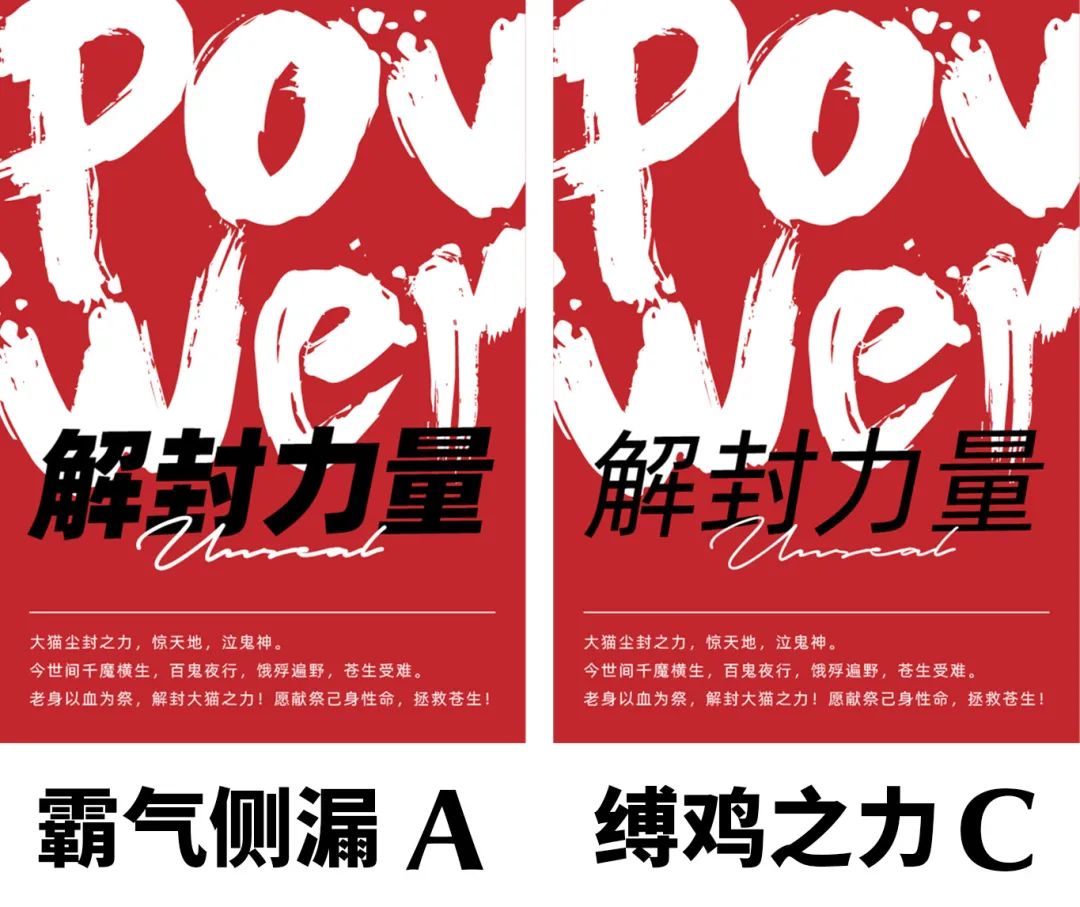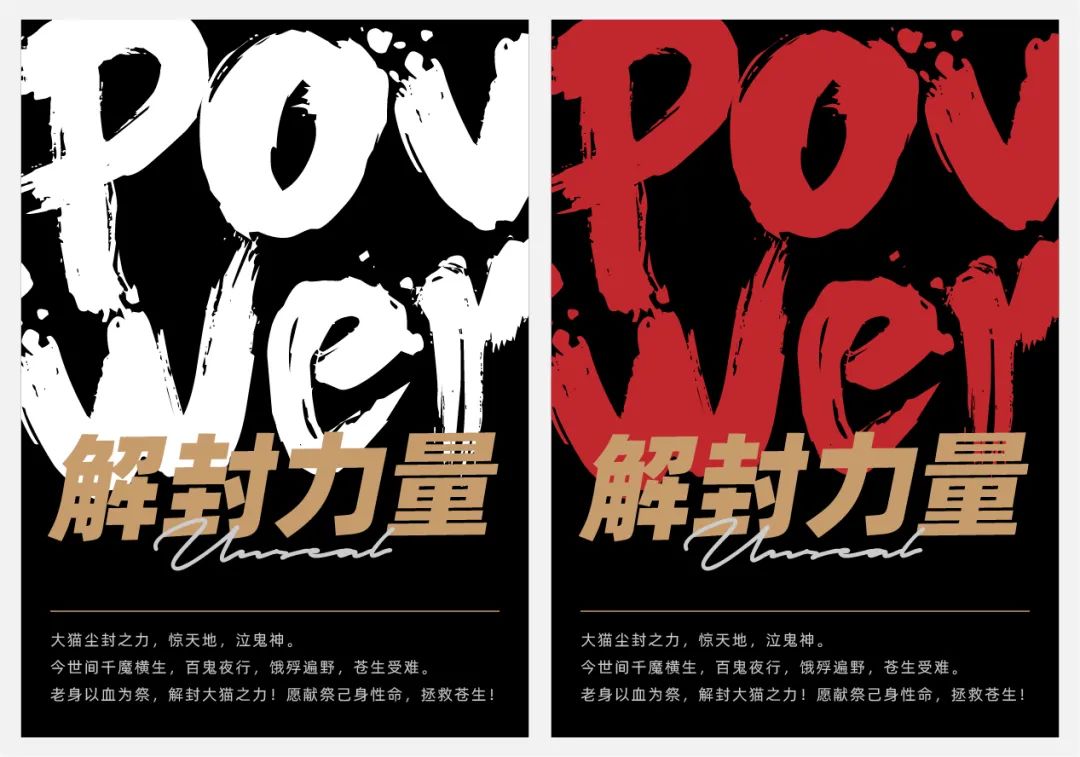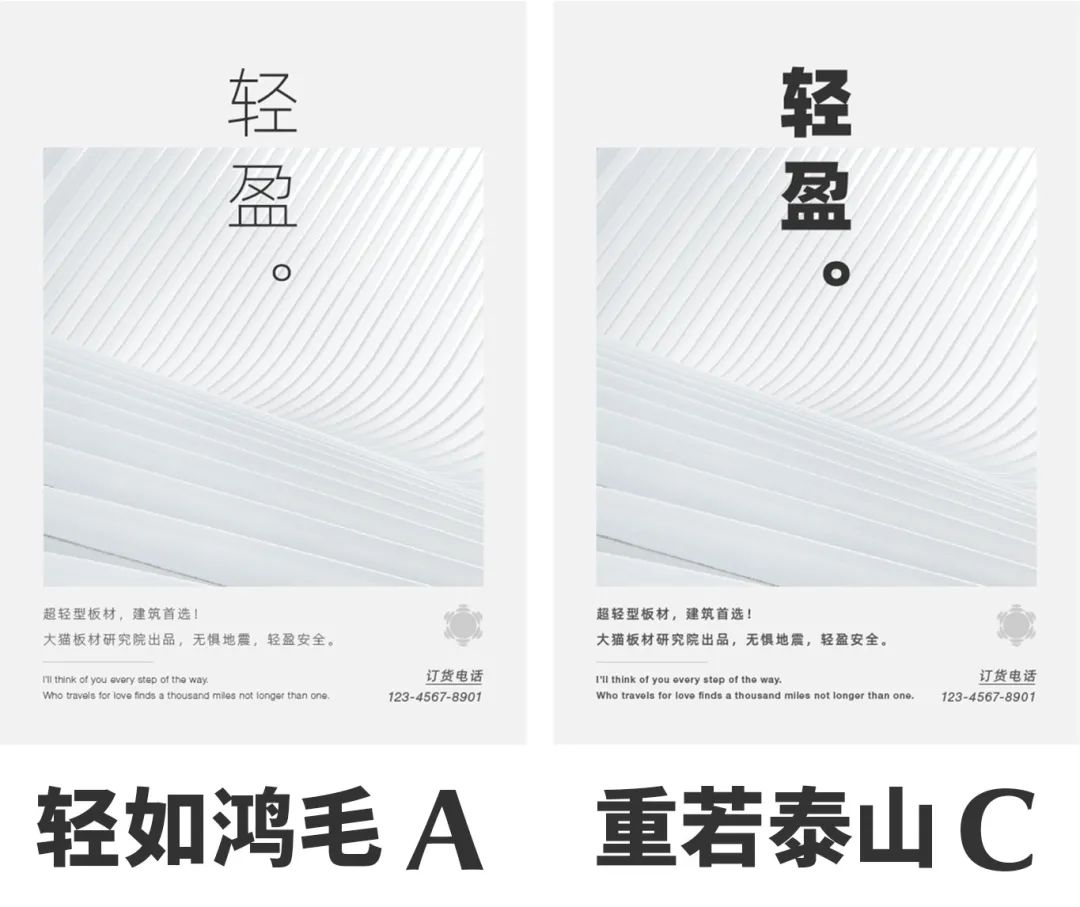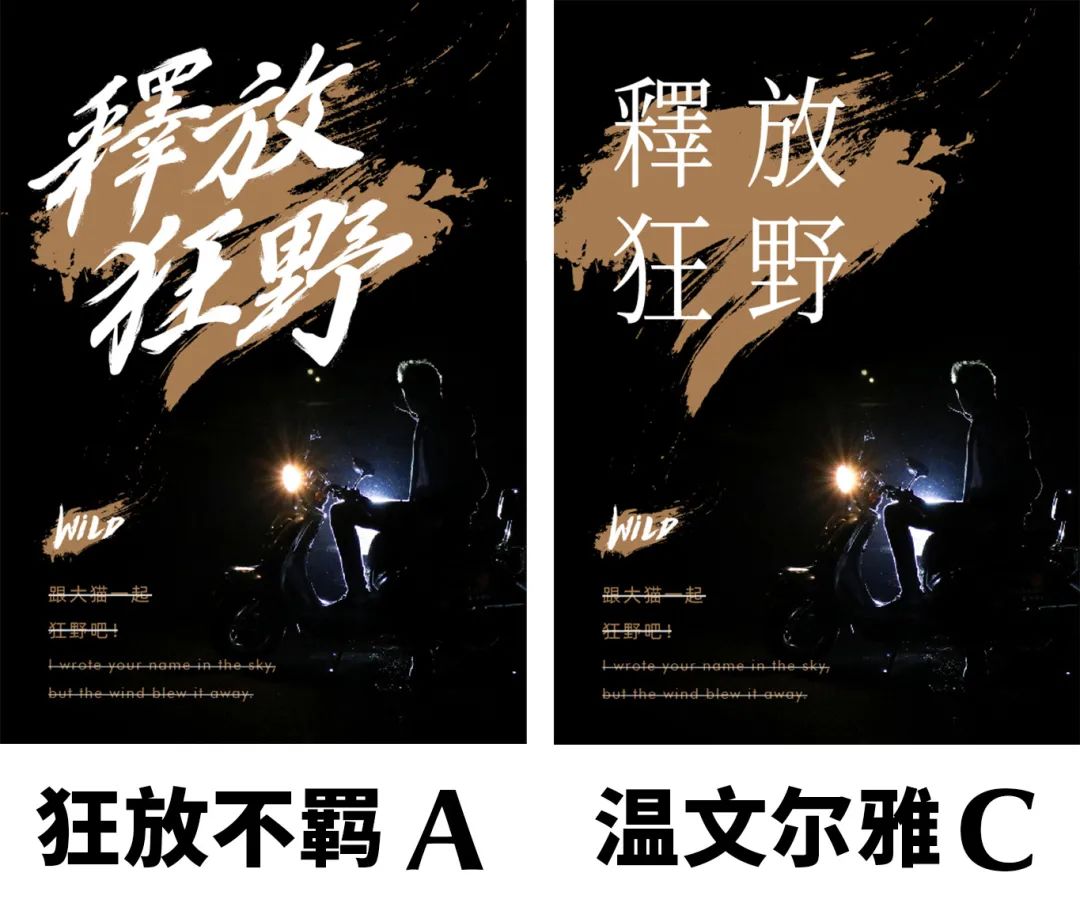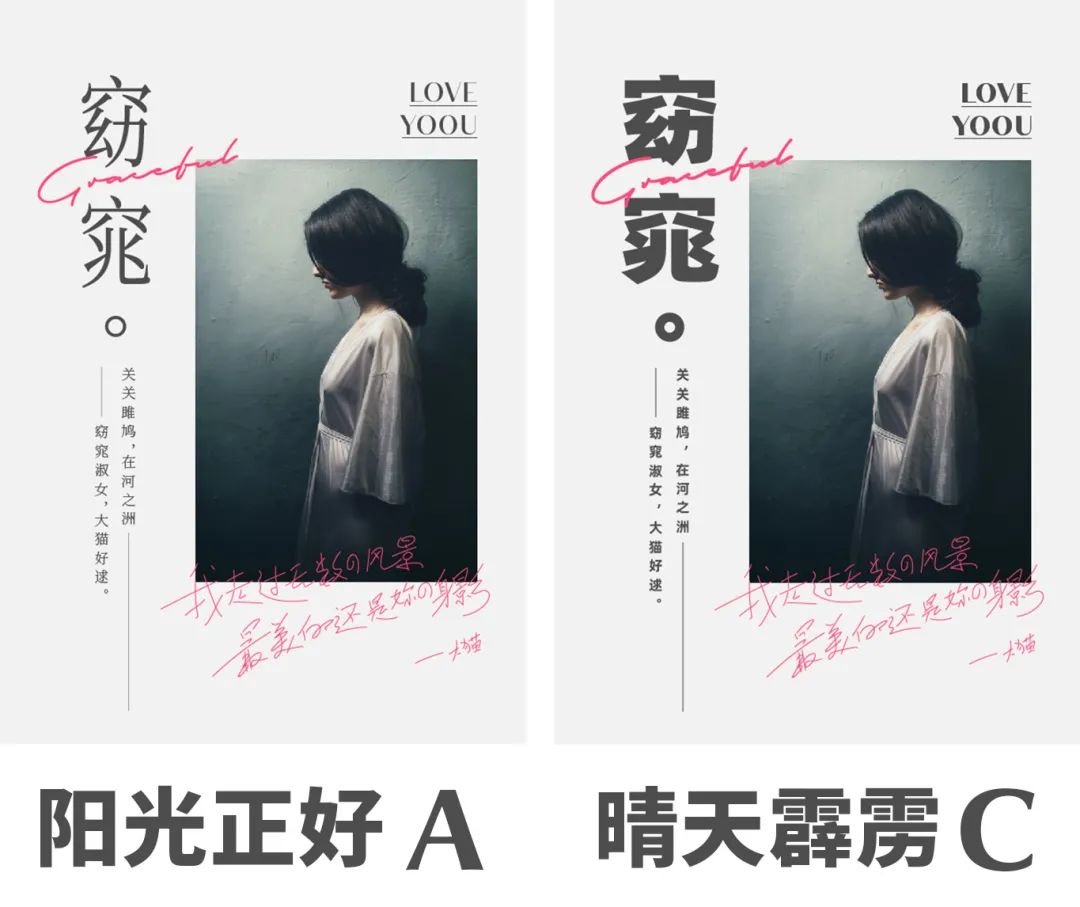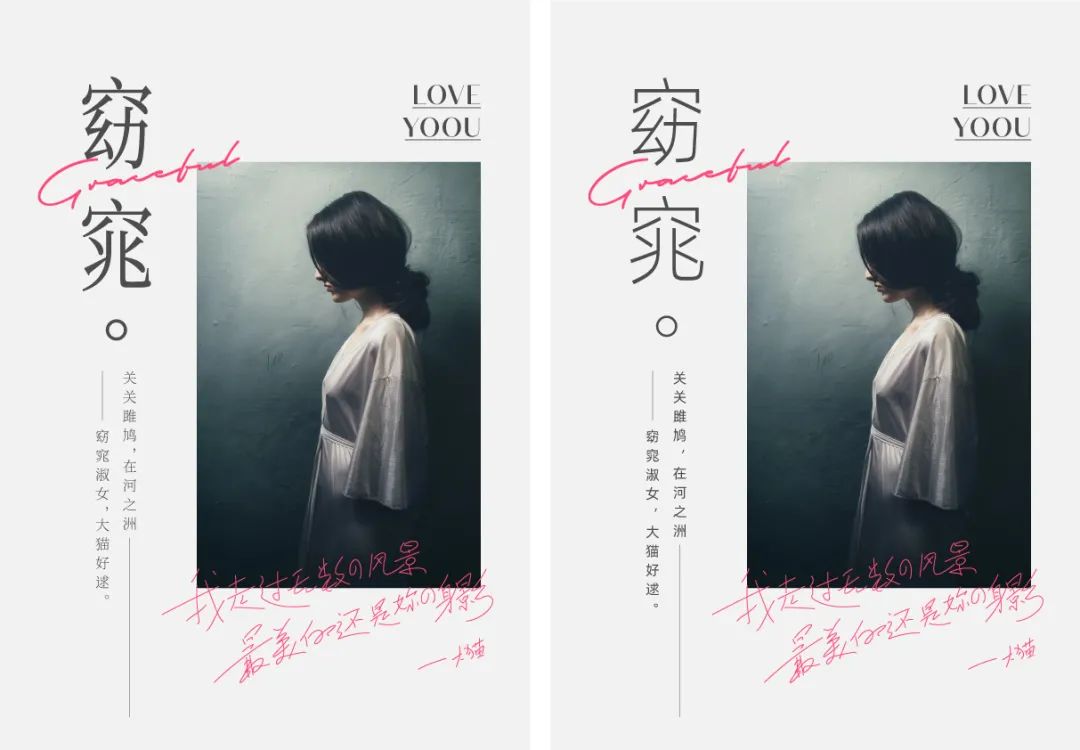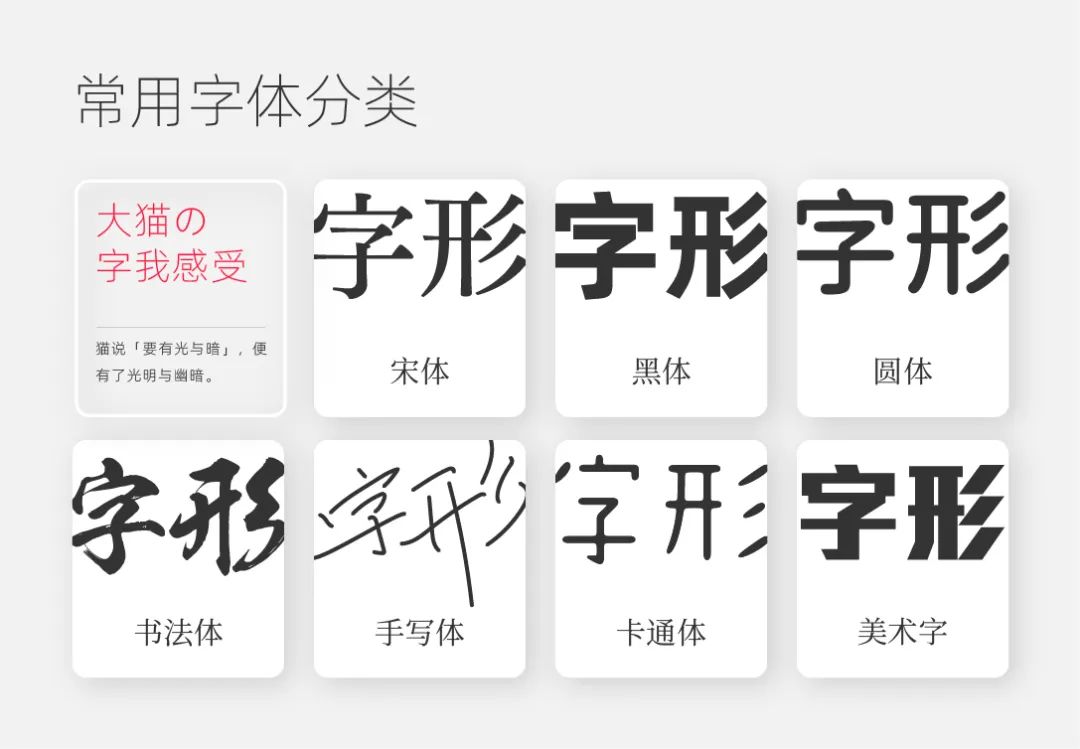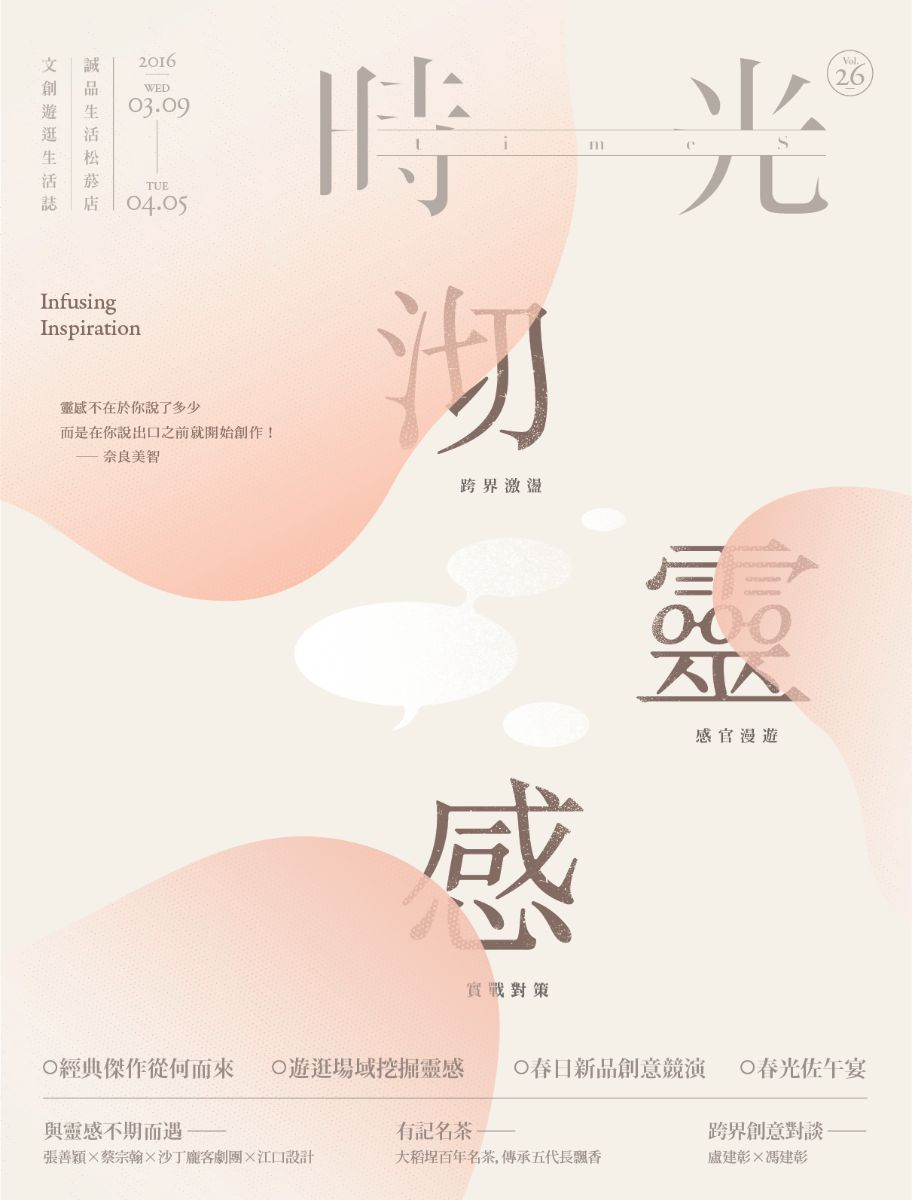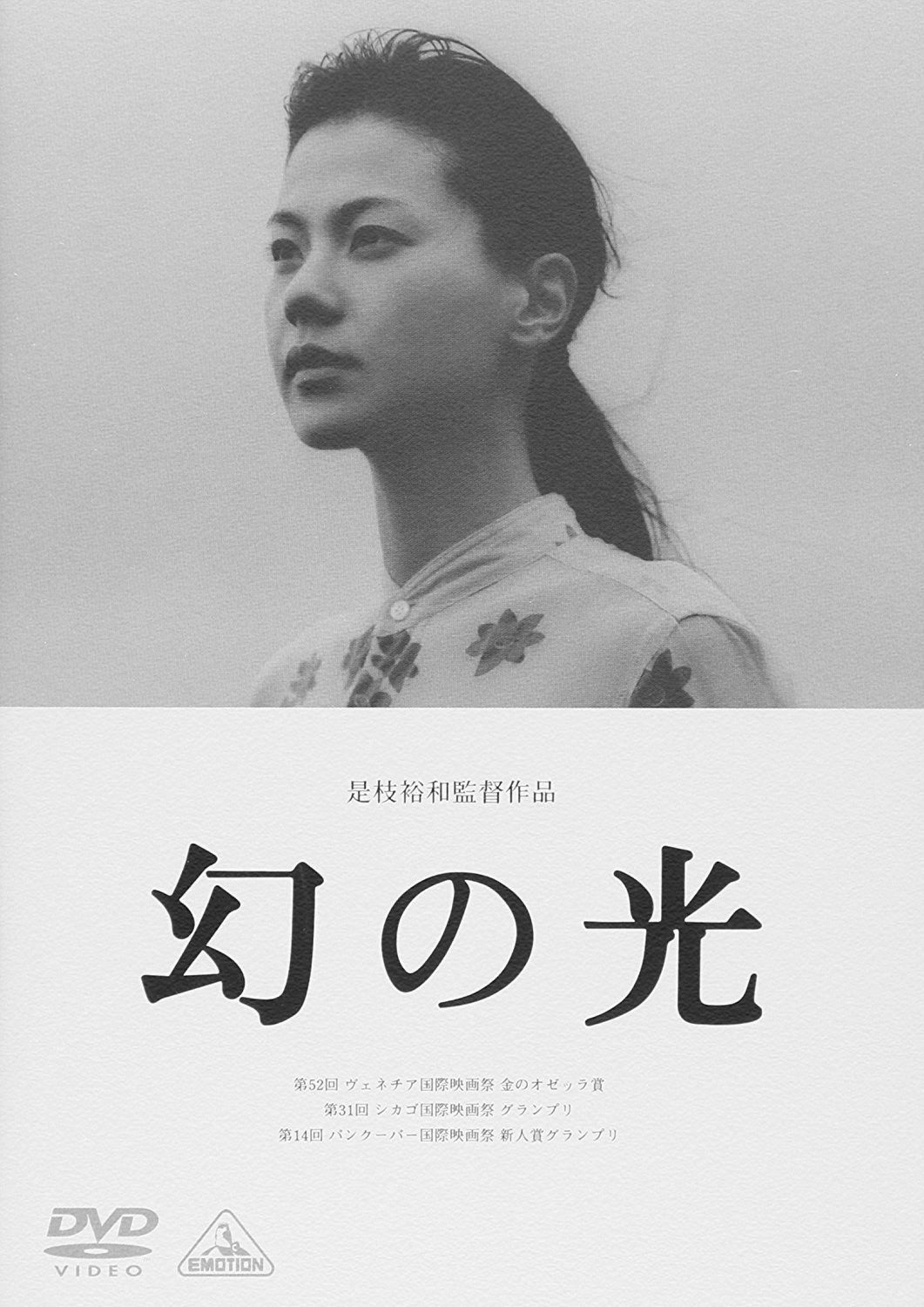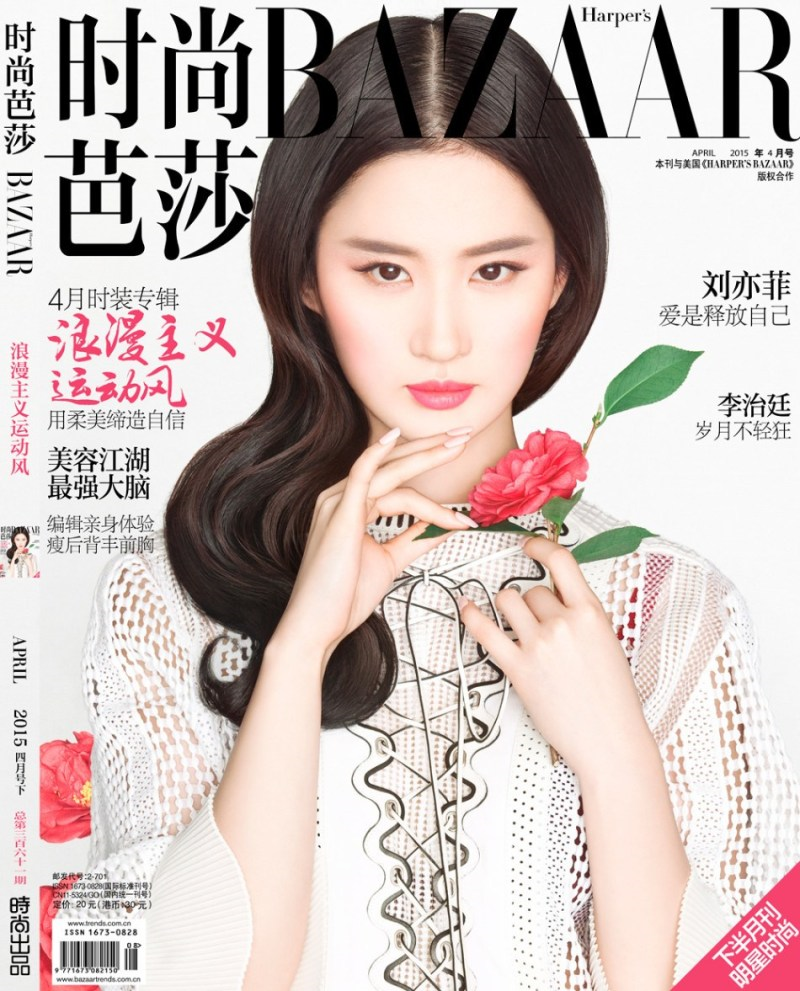
排版双修神功——字我感受(上篇)
万众期待中,星光璀璨里,寡人又乘风而来~
跨越山和大海,穿过诗和远方,带着它来了!
它,就是排版双修神功的第8章——字我感受!
本篇功法分为三部分,分别是字重、字型、距离。
因为此功法篇幅太长,咱分为两部分来讲~
今个咱就先讲一下字重和中文字型~
咱先来看第一部分 —— 字重。
照例,先来看俩问题~
为了更易理解,咱这俩问题案例,都用黑体来表现~
下面俩版面,哪个更具力量感?
一番感受下来,必须是「霸气侧漏A」更有力量感鸭!
「A」字体比较粗,比较厚重,看上去就更有力量感!
而「缚鸡之力C」那么细的字体,这叫“缚鸡之力”嘛?
这叫“手无缚鸡之力”才对,更别谈什么力量了~
把「力量」比作大招,字重比作蓝条,
「C」连支持放大的蓝都不够,
还解封,解封个寂寞~
这个例子告诉我们,粗壮就是力气大呀!
除了红底白字的爆发型力量,咱还可以改个黑金配色,让这力量尊贵起来~
不同的色彩,给人的心理感受也是不同滴,比如再改俩配色~
扯远了扯远了,这期修炼字体感受,啷个扯到色彩上去了~
关于色彩,咱有机会再详细说道
继续看第二个问题
下面俩版面,哪个更轻盈?
又是名字暴露了一切,肯定是「轻如鸿毛A」更轻盈嘛!
「A」的字体比较细,感觉没啥重量,自然就轻了!
而「重若泰山C」,这字体也忒粗了~
说它“轻盈安全”,俺可不信。
指不定用不了多久,寡人就要被砸了,
到时候不出人命就谢天谢地了,还妄求安全?
不买不买,坚决不买~
是什么传达了上述例子中不同的感受呢?
答曰:字重!
字重,说白了就是字体笔画的粗细程度~
细的字体,视觉上比较轻,没啥重量;
粗的字体,视觉上就比较重。
学名“字重”,也就是这么来的。
以思源黑体为例,它有七个字重,
这里寡人做了个图表,标明了不同字重的感受。
实际运用时,对照图表,选择契合项目气质感受的字重即可。
下面再看俩例子~
这个主题为「渐见,感透」,为了传达这种感觉,用的就是比较小的字重!
纤细的字体搭配干净的画面,这种感觉就成了!Nice~
「环太平洋」韩国版海报,下面的字体咱虽不晓得读啥,
但可以看到字的笔画是比较粗的,字重依然是比较大的!
恢弘大气的机甲画面,搭配力量感很强的大字重,
非常有Feel~非常和谐~
字重相信大家都晓得啦,
接下来进入第二部分——字型!
也是先来看俩问题~
下面俩版面,哪个感觉更契合主题?
主题是“释放狂野”,那必须是「狂放不羁A」更贴合主题呀!
毕竟「A」的命名就点题了!
认真系列:
两个画面的主题是一样的,只是标题字体不同,传达的感觉就很不同~
「狂放不羁A」用的是奔放的书法字,比较有气势,狂野感就强!
而「温文尔雅C」用的比较细的宋体字,给人感觉比较文艺、典雅。
「C」优雅是优雅了,但主题是“狂野”呀喂!
这字体是假的狂野,这版面明显也狂野不起来嘛!
(本喵喜欢狂野的,毕竟跟寡人一样放荡不羁~)
下面俩版面,哪个感觉更契合主题?
主题是“窈窕”,也就是“窈窕淑女”,
那必须是「阳光正好A」更适合呀!
为啥合适?且听寡人娓娓道来~
「A」用的宋体字,且比较高挑优雅,就契合“窈窕淑女”的气质。
那优雅,那美丽冻人,是寡人的菜没错了~
而「C」用的厚大粗重的黑体字,
这就不是窈窕淑女了吧,这是女汉纸呀,
一巴掌下来能把五指山劈烂的那种!
我等凡夫俗子铁定招架不住~
这时候又有爱卿说了:
上部分说小字重可以表现女性,
那这里用细一点的黑体可以不?
当然~可以!
虽然可以,但表现的感觉似乎跟宋体有所不同!!
较于宋体来说,
细黑体似乎少了点知性美和文艺气息,
反而多了些现代和理性的感觉!
所以有时候,选择什么字体,取决于你想赋予这版面什么感受!
你,就是造物主!
你想有光,便有了光;你想有暗,便有了夜!
(大猫中二病晚期,这段不用管~)
要说喜欢的话,本猫还是喜欢知性滴!
通过上述例子,咱晓得了,
同样的主题、同样的画面,仅仅是不同的字体,
就能传达出截然不同的感觉。
所以,
要想设计做的好,了解字体少不了!
选择对的字体,那就事半功倍!
只见你挥着皮鞭,大呼道:
告诉本宫,如何选择字体?
那架势,简直是风云变色,气吞山河呀!
寡人再不说,估计就要受皮肉之苦了~
慌了慌了,那就说道说道。
选择合适的字体,
关键在于了解不同字体造成的感受!
我们中文字体,基本可以分为这么7大类~
下面跟着寡人,咱们逐一讲解~
宋体,是宋朝出现,到明朝才完善成熟的,
所以,港澳台地区叫「明体」,日本那旮旯叫「明朝体」,
其实,都是特征一致宋体字~
宋体历史悠久,又具有一定的人文气息,
所以能传达传统、典雅、文艺的感觉。
这种文艺的感觉,简直就是大猫的翻版!
所以想表现这种感觉,就用宋体吧~
这张诚品书店的海报有很强的文艺气息~
正是宋体所带来的感受!
传统祭祀活动?那必须得抄起宋体就是干呀!
「艺术之道」当然得有文化感和人文气息,
用宋体字准没错!
要表现文艺优雅的感觉,宋体也是不二选择~
用宋体,给妹纸加点知性美吧!毕竟寡人喜欢,吼吼~
宋体可不可以拥有现代、时尚的感受?
其实是可以的~
宋体在横竖笔画对比度极大的时候,具有现代时尚感,如下面这几种宋体~
这种感觉的宋体,也因为其时尚感受,经常被用到时尚杂志上~
说完了宋体,咱再来说说黑体~
黑体,近100年才出现,还是西文中的无衬线体影响下的产物~
相对于宋体来说,可以说很年轻了~
如果你想传达理性、现代、简洁的感受,就可以选择黑体哟!
路飞在积攒怒气,他身后用的字体就是比较粗的黑体!
大字重的黑体让画面更稳重,也使力量感更强哟~
(大猫也是很有力量滴~)
学术类的严谨的版面,用黑体也是完全ok的!
能使画面看起来更专业、更严谨的说~
现在的黑体,基本上都是横平竖直,干净利落的。
但早期的黑体是有喇叭口的,为撒子呢?
主要是早期,机器精度不高,加入喇叭口可以防止照排时的失真~
随着技术进步,现在已经不存在这个问题了!干净利落的现代黑体也成了主流。
但如果你想在现代简洁中,加入一点复古感和人文气息,
就可以选择「喇叭口黑体」~
像这个,理性中又带有一点人文气息。
就是喇叭口黑体带来的感受啦!
跟着寡人,再来看看圆体~
圆体是在黑体的基础上演变而来,字形的结构跟黑体比较相似,
只是笔画造型更圆润!
那么圆体有什么感受呢?
圆体的现代感跟黑体差不多~
不过相较于黑体,圆体更丝滑圆润,
另外没啥棱角,感觉比较舒适~
除了上述感受,
圆体在小字重时具有女性感,这点跟字重那部分同样的原理,
但在大字重时会有更多的儿童属性,比较俏皮。
这个海报用的圆体,搭配浅色的背景,感觉十分舒适,
丝滑顺畅,让人心情舒畅咯!
大字重下的圆体,卡通感也比较强,适合表现一些趣味性的画面哟!
说到趣味,就不得不提「大猫的灵魂了」
咱继续,说说书法体~
这里发书法体特指毛笔书法。
书法体大气磅礴,非常具有文化底蕴。
毛笔字给人的感受一向是比较厚重的!
书法的历史,绝不比宋体短,
当然也就有很强的文化传统和历史底蕴~
行书书法字气势恢宏,颇有波澜壮阔的感觉~
(大猫也是气势如虹呢)
所以想表现上述的感觉,用书法字准没错~
像这个,画面虽然简单,但是书法体一出,顿时就有气吞山河之势了!
这气势,是有道友在此渡劫呀~
只见那猫左手一抬,顷刻间天崩地裂,
一股毁天灭地的能量直上云霄,抗击雷劫!
打击乐音乐会的海报用了书法字,放肆激昂!
把那敲击与激情表现的淋漓尽致~简直就是爆裂鼓手有木有!
「青春大卫」海报。青春嘛,不放肆怎么叫青春?
这个书法字确实很放肆ヾ(≧O≦)〃嗷~
(啊,夕阳下摔(fang)倒(dang)的身影,是大猫儿逝去的青春~)
动作片、武侠片电影海报也是经常使用书法字滴!
毕竟气势如虹,江湖气息浓厚~
使寡人忆起当年,
一人一剑丈天涯,快意恩仇江湖间~
虽说书法字气势如虹,
但不同的书法体也要分类讨论。
比如,
比较安静的、没啥飞白的楷书和隶书,
传统感和文化底蘊感都有,
但相对于行书等比较张扬的字体来说,气势上输了很大一截。
原研哉设计的这个酒标签,用的就是不太张扬的书法字,
因为没必要体现张力与气势,只把历史和底蘊感表现了就可以了~
所以,选字还要细细去品~
猫说:设计要活,莫要一条路走到黑~
继续,说道说道手写体~
手写体,就是指不加雕琢的手写字。
字库里的手写字,跟实际的手写体还是有很大差别的,
毕竟,字库字是单个的字,无法模拟字与字之间的笔画连带关系~
30s写的,没细调,大家凑合看个意思,哈哈~
所以,如果用手写体,
寡人更推荐自己写!这样才是最有温度的~
手写体最大的特点就是随性,
根据不同的写法,会出现不同的风格~
可以青春放肆,亦可以岁月静好~
其次,手写体是很亲切的!
可以说亲和力相当高了~
毕竟手写字,是有温度,有情绪的,
不像黑体或宋体那版冰冷。
手写体有温度,有亲切感和烟火气!
如果改成右图的黑体,虽然更醒目了,
但却冰冷了,机械了,无生趣了~
醒目或者美观,才不是设计的唯一标准。
更多的时候,要设好目标,
找准想传达的感受,一刀入魂~
说到烟火气,
寡人又想到了,
之前刷爆盆友圈的,
设计师爆改菜市的活动。
改后的菜市,确实干净整洁了,
却也没了人间烟火气。
如今繁华不再,生意惨淡,失去了生活的印记~
大多数人,还是喜欢烟火气强的菜市~
又扯远了又扯远了,
总之,
设计归设计,但莫夺走生活本身~
百乐笔的海报,标题直接是用百乐笔写出来的!
既亲切,又直接体现了产品能力!
「五月天·第二人生」的专辑设计,聂永真作品。
手写的字体非常有感觉,洒脱、艺术范,
将专辑调性表现的淋漓尽致~
同样是聂永真作品,
这个榨汁机海报所用的手写体,很随性洒脱,仿若涂鸦!
但这种放肆和张力很契合主题~
这个手写体用在这里,挺有诗意,
挺诗和远方的~
卡通字相对于普通的字体,结构跳跃,大小不同,
且东倒西歪,看上去不是很严谨。
但也是因为这,卡通体很活泼、很有趣,且能够很好的营造轻松活泼的氛围。
卡通体淘气、活泼,是表现趣味和轻松的不二之选!
趣味的画面,搭配趣味轻松的卡通体,很对味吧!
Ps:上面的标题字虽然是宋体的笔画特征,
但结构是大小不同,高低跳跃的,而这正是卡通字的重要特征,
所以字体依然很有趣味,算作卡通体~
儿童插画,自然也要搭配能代表童真轻松的卡通体啦~
旅游的海报,上面的字体用的依然是高低跳跃的卡通字形~
毕竟旅游是愉悦轻松的,而卡通字最能彰显这种氛围~
这种氛围,就跟看大猫儿的文章一样,快乐源泉哟!
所以鸭,
要想设计做的好,
了解字体少不了!
动手之前,想想好要传达的感受,
根据感受去选择合适字体,
铁定是错不了滴!
下篇内容:美术字、英文字型、距离、复合字体。